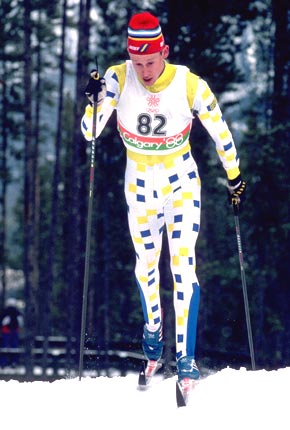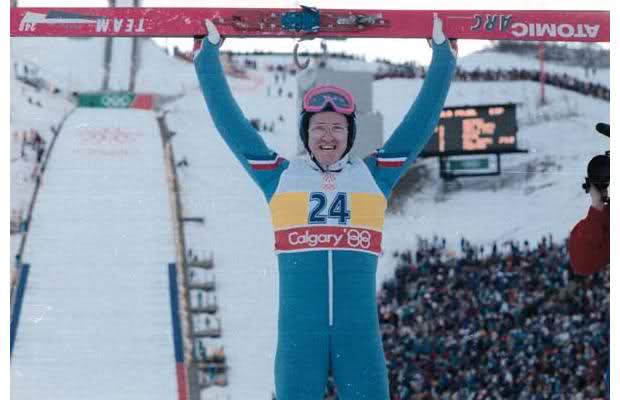
suche 2 schriftarten
ich suche die Namen dieser Schriftarten:
- die Erste ist eine Schriftart, die häufig im Wintersport (besonders im Biathlon) als Startnummer verwendet wird, war auch bei den Olympischen Spielen in Calgary '88 verwendet...
-die zweite war im offiziellen Logo der Fußball-WM 1994 verwendet:
Die Startnummern-Ziffern haben etwas Ähnlichkeit mit der ITC Eras von Boton, allerdings dürfte die Inline/Kontur nachträglich angelegt sein.
Es gab vor mindestens 20 Jahren mal eine Kontur-ErasBlack als Transferschrift von einem amerikanischen Hersteller, aber im Internet hab ich nichts mehr gefunden, außer dass die Eras auch als Erie und anders dort herumschwirrt, sogar noch gerade gestellt (!).
Bei der Startnummer-Schrift handelt es meiner Meinung nach nicht um die Eras, obwohl etwas Ähnlichkeit zu merken ist, die "2" ist aber im vergleich mit Eras ziemlich anders...